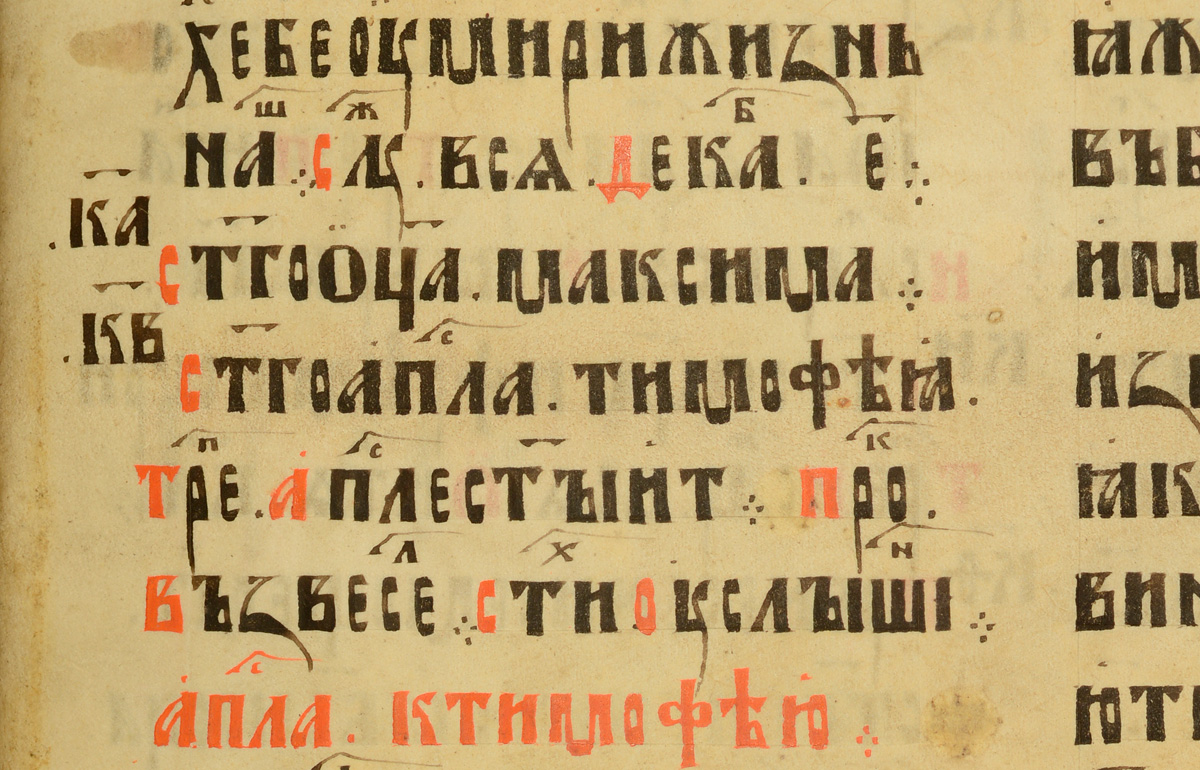
Кириллица – своеобычная письменная система славян
Кириллица – это широко распространенная у восточных и южных славян, а также некоторых соседствующих с ними народов письменность.
Кириллица, как алфавит применяется для записи слов, а в Средине века и чисел. Кириллица получила свое название от имени известного просветителя славян Кирилла. Он, со своим братом Мефодием создавал для славян азбуку в конце IX века. После принятия христианства кириллица стала основной и официальной письменностью Руси.
По существу современное понятие «кириллица» имеет несколько, связанными со славянской словесностью толкованиями:
- Кириллица (поначалу одновременно с глаголицей) являлась старославянской азбукой древнеславянского языка.
- Совокупность письменных систем и алфавитов разных языковых групп имеющих в основе старославянское кириллистическое письмо.
- Традиционный церковный полууставной шрифт для печатания богослужебных книг (как противопоставление петровскому шрифту).
Кириллица была основана примерно в 863 году братьями Кириллом и Мефодием – уроженцами греческого города Салоники («солунские братья»), положивших жизнь на проповедь христианских ценностей славянским язычникам. За основу алфавита братья взяли греческое уставное письмо, к нему добавили несколько букв, характерных для уникальных звуков славянского говора.
Получившаяся азбука представляла собой письмо, ставшее традиционной кириллицей. Из 43 букв (элементов), 24 из греческого алфавита, а оставшиеся 19 элементов изначально имели славянское происхождение. Братья-проповедники в основном свою миссионерскую деятельность осуществляли в Великой Моравии. Там алфавит прошел успешную апробацию в славянском государстве и начал распространение в среде родственных народов.
На Руси кириллица нашла свое применение незадолго до Крещения 988 года. Первыми записями на кириллице в молодом русском государстве были внешнеполитические договоры и соглашения, а также архаичное хозяйственное делопроизводство. Первыми рукописными книгами на кириллице стали богослужебные списки и тексты. Форма начертания кириллицы X –XIV веков называлась «Уставом». Ее отличали:
- прямолинейность;
- удлинение букв снизу;
- крупный размер;
- отсутствие пробелов между словами.
С XIV по XVIII века развивался «полуустав», отличавшийся от устава:
- округлостью и размашистым начертанием букв;
- удлинениями снизу ми сверху;
- появившимися знаками препинания;
- надстрочными знаками;
- малым размером.
Появившаяся в XV веке скоропись способствовала упрощению и удобству стиля письма. Линии букв стали равновесными, возникла и получила развитие витиеватая вязь (для оформления заглавий).
Пётр I привнес в процесс развития кириллицы новый гражданский шрифт и существенные изменения в алфавите. Многие буквы стали более пропорциональными, не обошлось без введения латинских букв «s» и «i». Русские буквы («ъ», «ь» и другие) выделялись высотой. Кириллица совершенствовалась до 1917 года эволюционно в направлении совершенствования гражданского и создания академического стилей.
После Октябрьской революции была проведена широкая реформа правописания. Буквы i, ъ (ять, ер) и Θ (фита) из алфавита были изъяты. В итоге сегодня кириллица в России имеет 33 буквы и полностью решает задачи для развития русского языка, стоящие перед современным алфавитом.